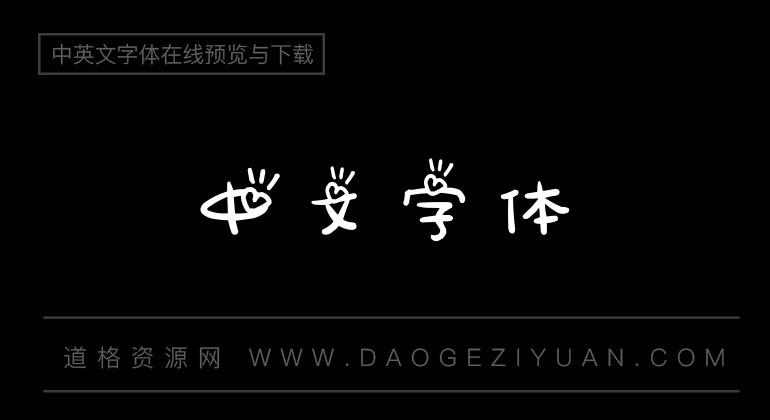
冬日暖心
? 冬日暖心字体是一款粗体手写字体,拥有流畅曲线和灵动笔画,充满温暖和柔和的气息,能够把温馨的感觉带给你。它的字体粗细恰到好处,可以让你的文字更加明亮,更有表达力。它的字体风格温柔而又充满活力,可以让你的文字更加有趣,更加富有表现力。
冬日暖心是一款非常不错的手写艺术字体,具有很好的视觉感,适合于文化类的宣传设计、商业类品牌的广告和产品包装设计以及个性化文字排版等较多场景。
冬日暖心字符映射图